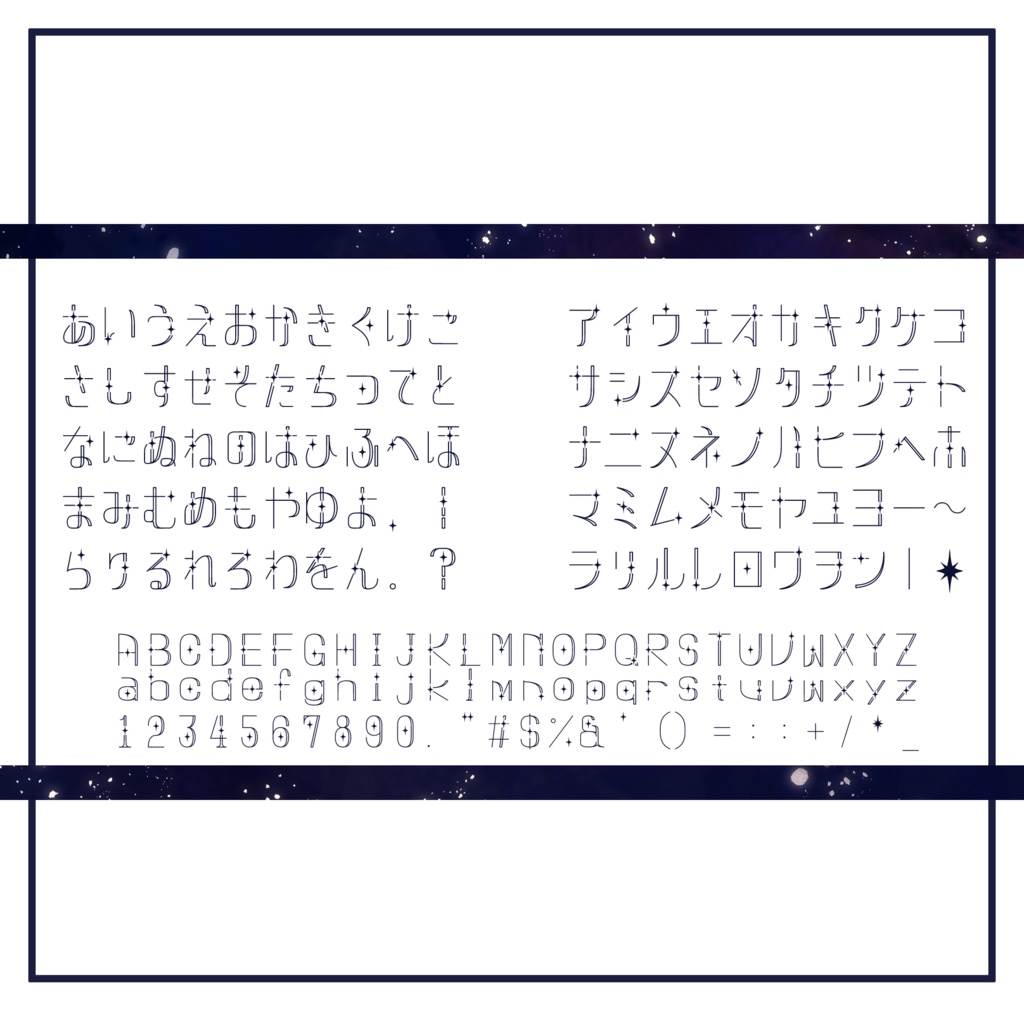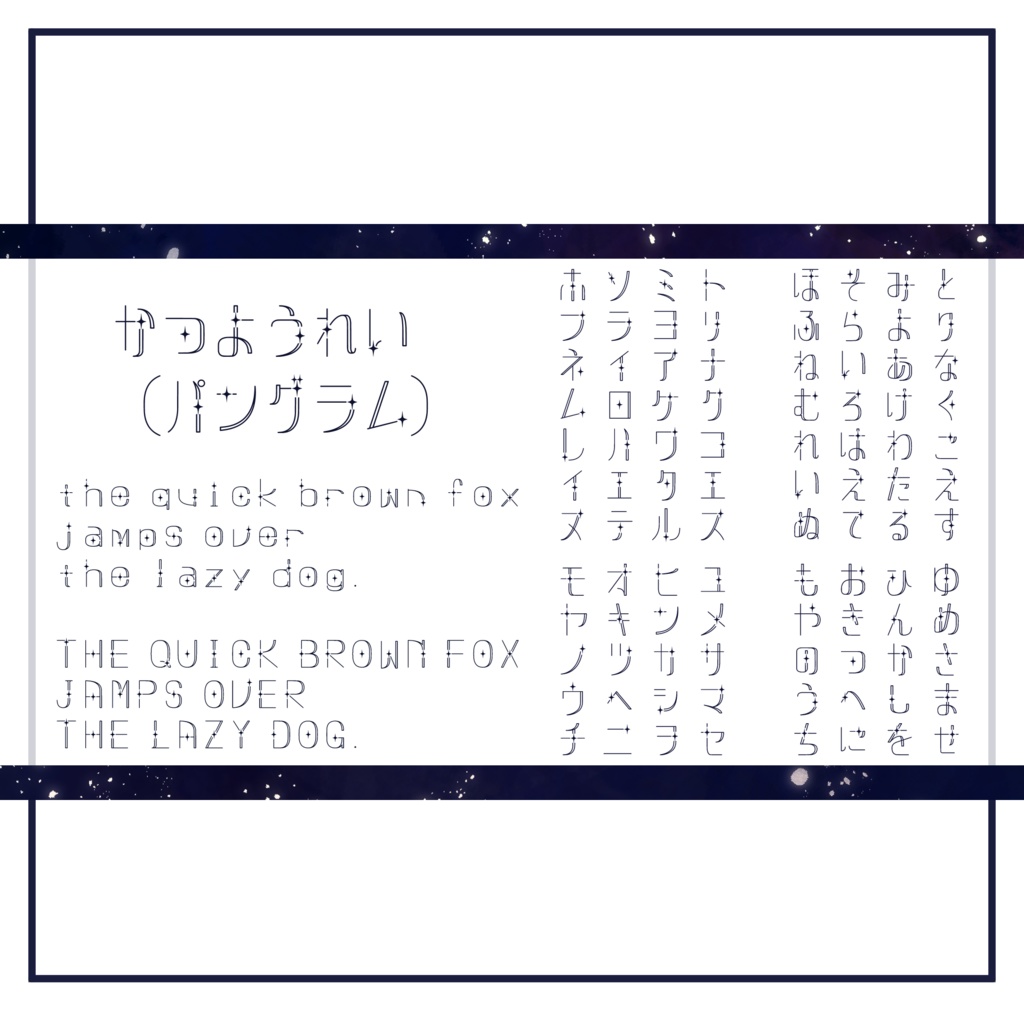
星めぐりフォント
星めぐりフォント 星座や星の光の見え方をイメージして作成したフォントです。 かな・カナ・アルファベット大小・数字・一部記号対応 記号は半角のみ反応するものもございます(漢字は非対応です)。 ttfファイルで配布を行っております。 ※2025.10.13 otfファイルの追加をいたしました。 最初にDLされた方のためにttfファイルも同時にzipファイルに梱包されていますが、otfファイルでのDL・使用を推奨します。 ◇利用について 商用・加工/変形可。 デジタル・印刷物問わずご利用いただけます。 利用に際して報告は不用ですがお声掛けをいただけると飛んで喜びます。 ◇注意事項 本フォントの著作権はしそめし本舗(ゆかりごはん・genshi39)が所有します。 名義を偽っての再配布等はお控えください。 本フォント自体の問題を除き、本フォントの使用された場面で起こったトラブルなどへの対応は致しかねます。 フォントファイルは更新される場合がございます。 ◇その他 挙動のバグなどありましたらマシュマロなどからご連絡くださると幸いです。 ◇更新情報 2025.10.13 otfファイルを追加配布